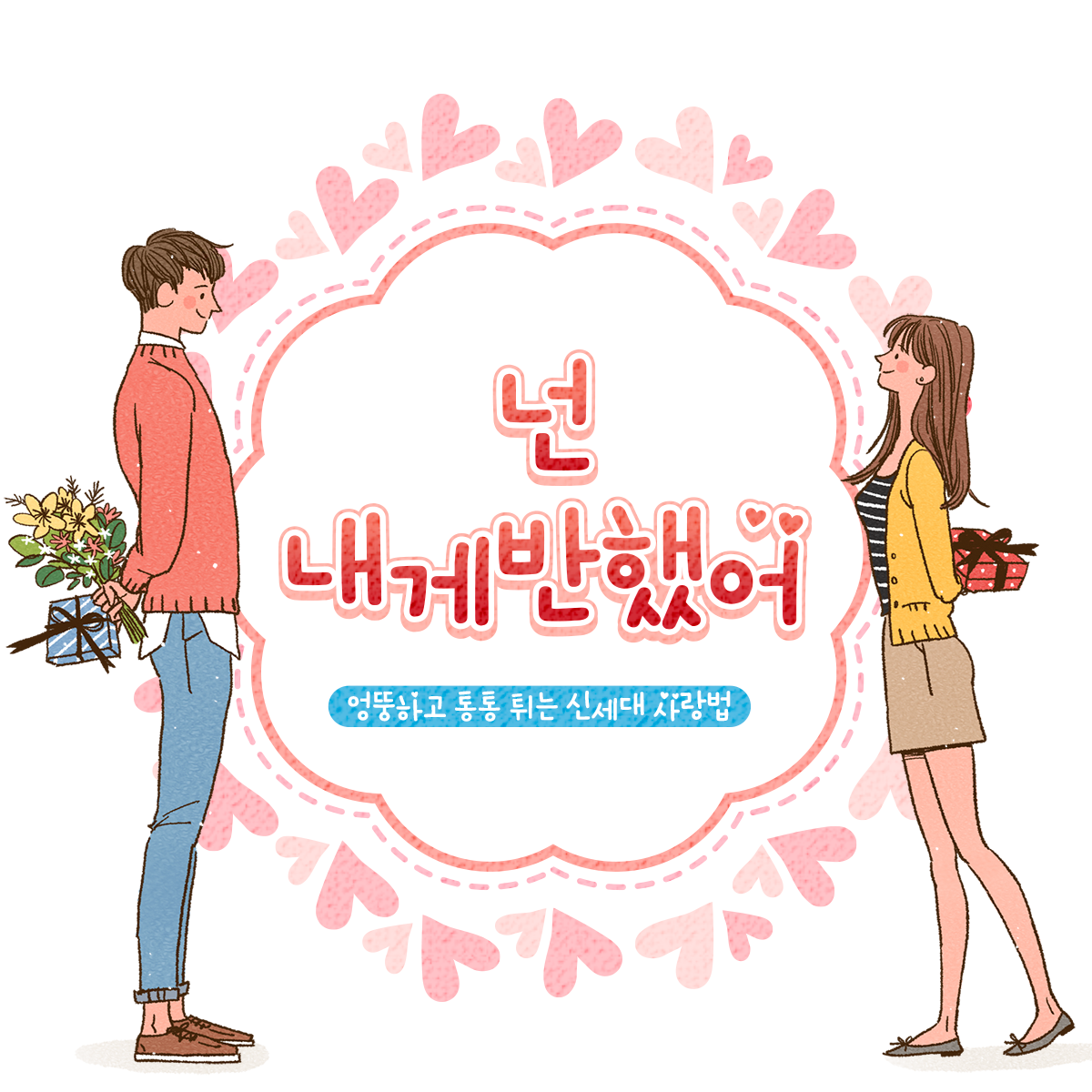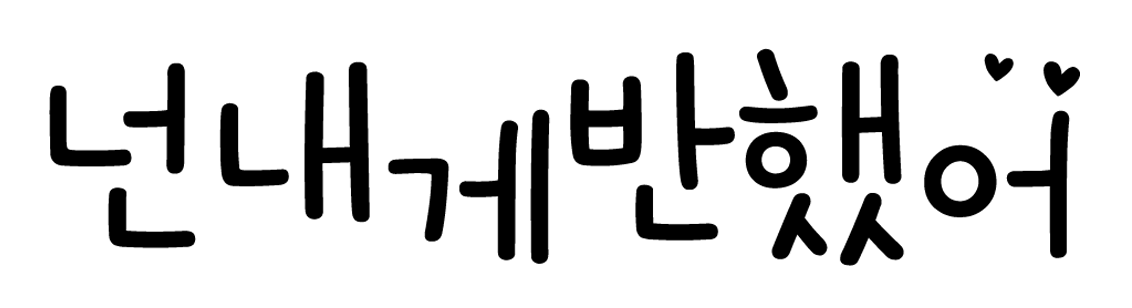
Sandoll 넌내게반했어
산돌 넌내게반했어는 자연스런 손글씨에 개성과 엉뚱함이 담긴 폰트이다.
부드러운 느낌의 글자이지만 정렬되지 않은 자유로운 글줄에서 어디로 튈지 모르는 개성과 엉뚱함을 느낄 수 있으며 포인트로 하트가 나비처럼 날아다니는 효과를 적용하여 신세대의 풋풋한 사랑을 표현하고자 하였다.
• Sandoll 넌내게반했어 / Sandoll Banhaetseo